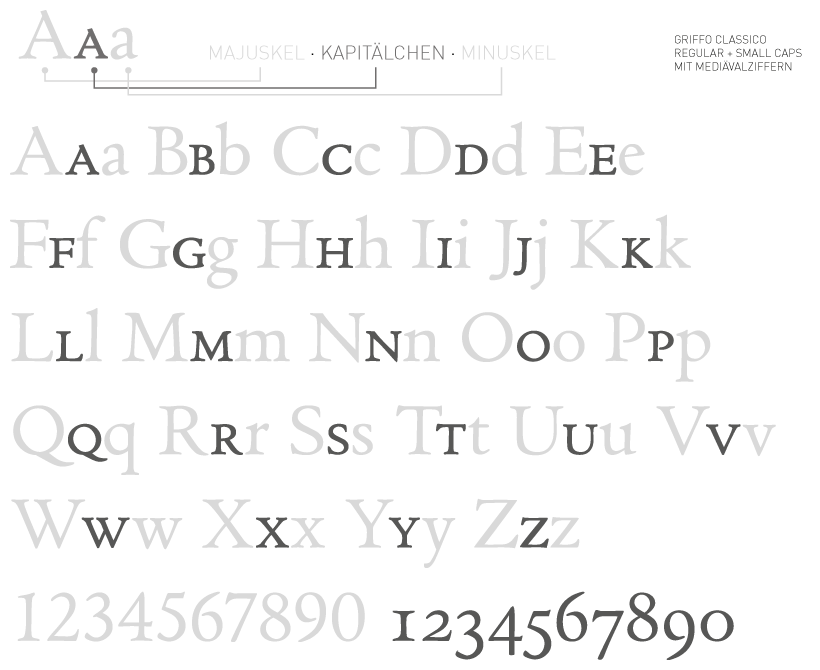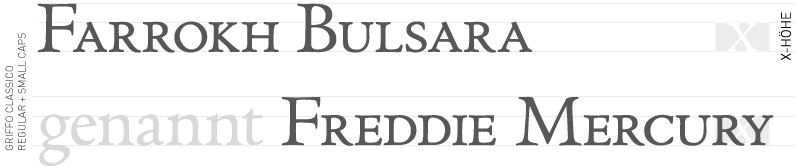
Kapitälchen (von lat. ‚capitalis‘ = „den Kopf betreffend“, engl. Abkürzung ‚small caps‘ von ‚small capitalis‘) sind Buchstaben, die die Form von Großbuchstaben in der Größe von Kleinbuchstaben haben und wie Kleinbuchstaben verwendet werden. Kapitälchen werden eingesetzt, um einzelne Wörter oder Wortgruppen wie Eigennamen oder Buchtitel hervorzuheben.
Bei der Schrift handelt es sich derzeit noch um einen eigenstädnigen Zeichensatz, den man gesondert erwerben und installieren muss. Die Schrift wird im Schrift-Menü als „Small Caps„ „SC“ oder „Capitals“ bzw. „Kapitälchen“ angezeigt. Kapitälchen brauchen einen etwas größeren Buchstabenabstand als normale Kleinbuchstaben (Gemeine): sie werden gesperrt. Bei normalem Buchstabenabstand würden sie eingeengt wirken.
Die OpenType Technologie ermöglicht seit langem die
Einbettung der Kapitälchen in den regulären
Schriftsatz.
Sehr wenige Schriften werden jedoch
mit diesem Kapitälchen-Umfang im Regular-Schnitt
ausgeliefert. So sollte man meist den Expert Zeichensatz
verwenden, um die echten Kapitälchen einsetzen zu können.
Vorsicht beim Einsatz der Kapitälchen in den Textverarbeitungsprogrammen, wie z. B. Microsoft Word™. Diese Anwendung verwendet keine Kapitälchen (auch wenn verfügbar!), sondern benutzt den Majuskel-Zeichensatz und verzerrt diesen elektronisch. Aus diesem Grund raten wir von der Verwendung von Kapitälchen in den Textverarbeitungsprogrammen dringend ab.
Im
HTML Code ist der Einsatz von Kapitälchen möglich
und geschieht mittels CSS-Befehl: font-variant:
small-caps;
Auch in diesem Fall werden die
Schriften lediglich gerendert und verzerrt; auch hier
wird kein echter Kapitälchen Zeichensatz verwendet.